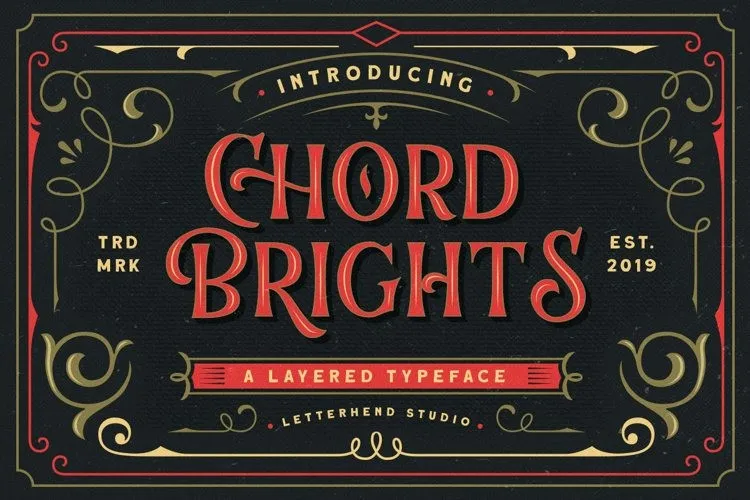
A Chord Brights Font é uma opção ideal para quem busca trazer um toque nostálgico ao seu projeto visual. Inspirada nos estilos das placas e anúncios do início dos anos 80, essa fonte de estilo display possui quatro camadas diferentes: inline, regular, outline e shadow. Sartstudio criou essa singular combinação única para oferecer um nível a mais de personalização aos designers. O seu design retro não só se destaca em projetos voltados para temas vintage ou retro, mas também é complementado por ornamentações extras que podem ser facilmente adicionadas com apenas um clique. A Chord Brights Font é perfeita para quem busca trazer uma pitada de nostalgia e simplicidade às criações digitais.